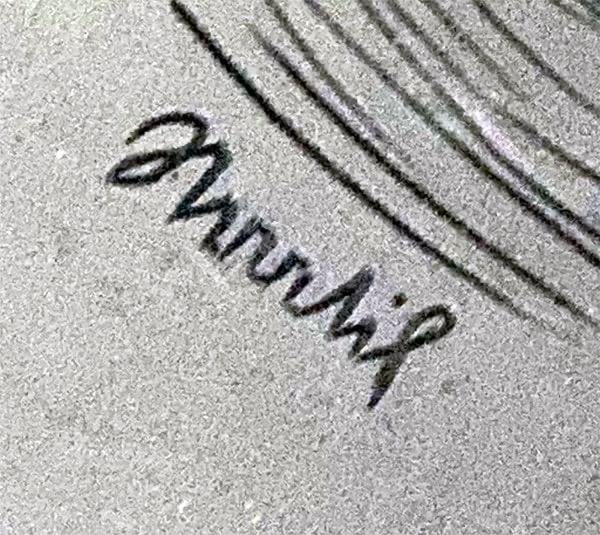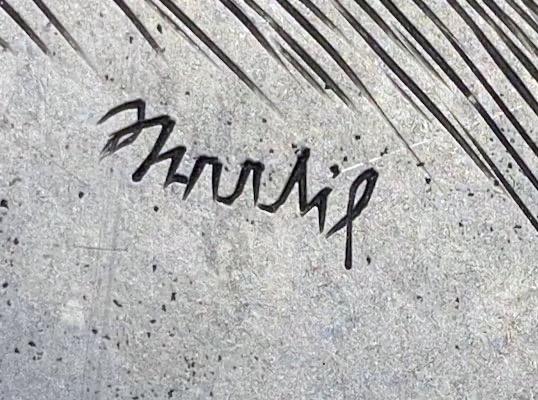
Künstlersignatur in Bleischnitten
Ich schau mir grad ein paar Beispielalphabete an und da tut sich mir die Frage auf, weißt Du, aus welcher Sprachregion der Autor kommt?
Der zweite Buchstabe weckt in mir die dringende Erinnerung an ein r. Dann passt aber das N nicht, sofern es ein ausgeschriebener Name sein soll. Ralf, hast Du noch mehr Daten zur Einordnung? Wirklich Blei oder vielleicht doch Kupfer, Stahl, wasweissich? Zeitraum der Entstehung? Thematik des Dargestellten? Eher Künstler oder mehr Auftragsarbeit (wie eine Illustration in Sachbuch)?
Oh, und Größe der Signatur im Vergleich zum Bild könnte vielleicht noch hilfreich sein. Ich bin da grad auf der beqeumen Seite und stelle mir eine "versteckte" Signatur eines angestellten Graphikers aus einem Offizin vor.